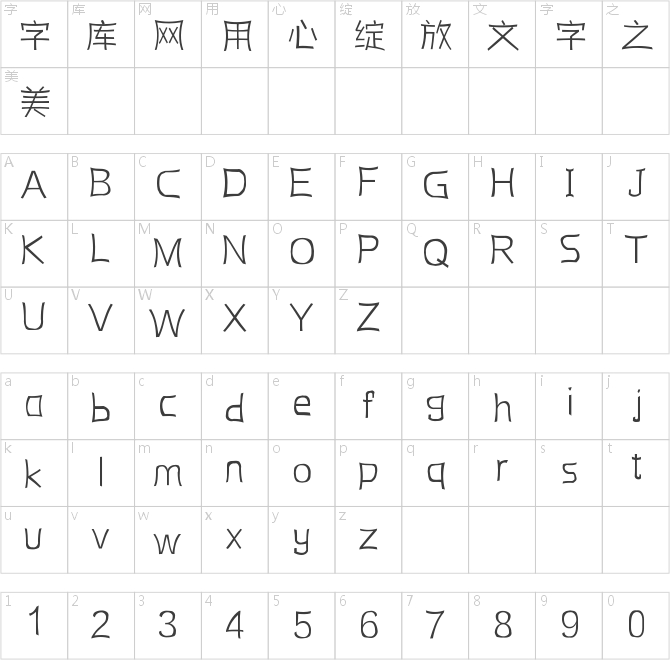
字體名稱(chēng): 幾何板凳體
幾何板凳體
幾何板凳體介紹
幾何板凳體字體字庫(kù)是一款讓人賞心悅目、百看不厭的中文字體,適合各類(lèi)廣告和產(chǎn)品包裝設(shè)計(jì)應(yīng)用,字體大小9.22MB,格式為ttf字體,上傳用戶(hù)是凡客,作者/版權(quán)方為未知